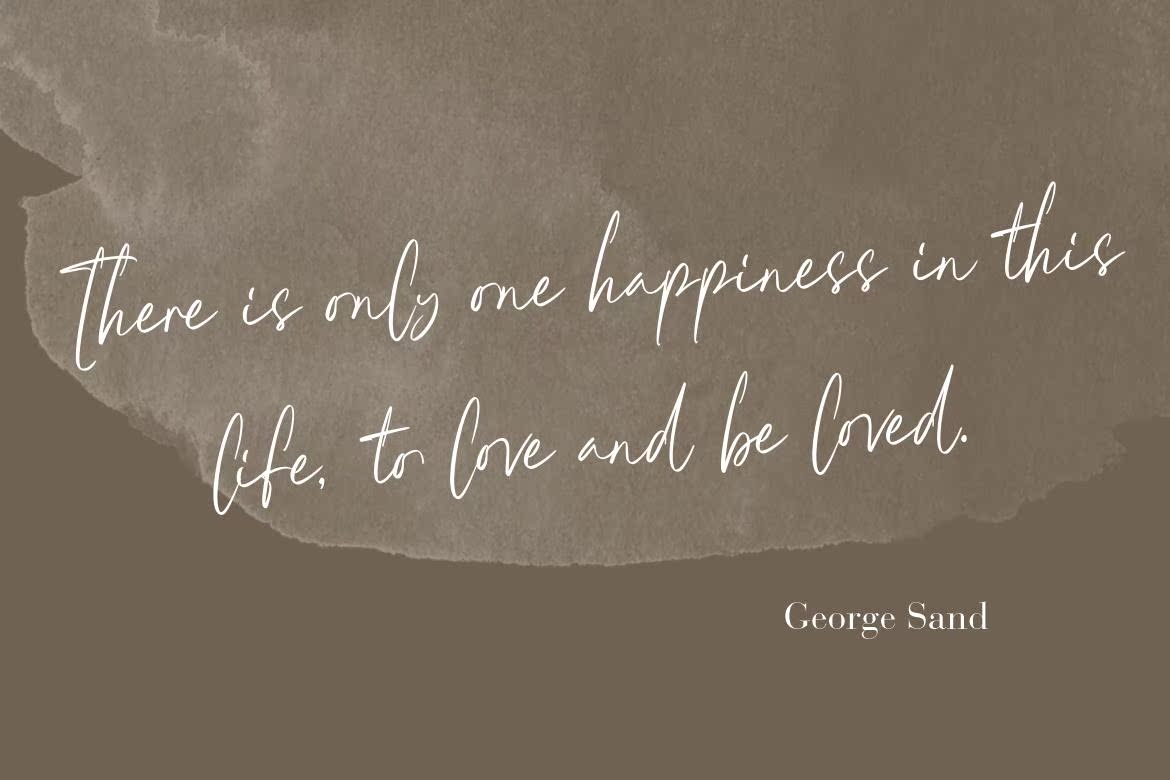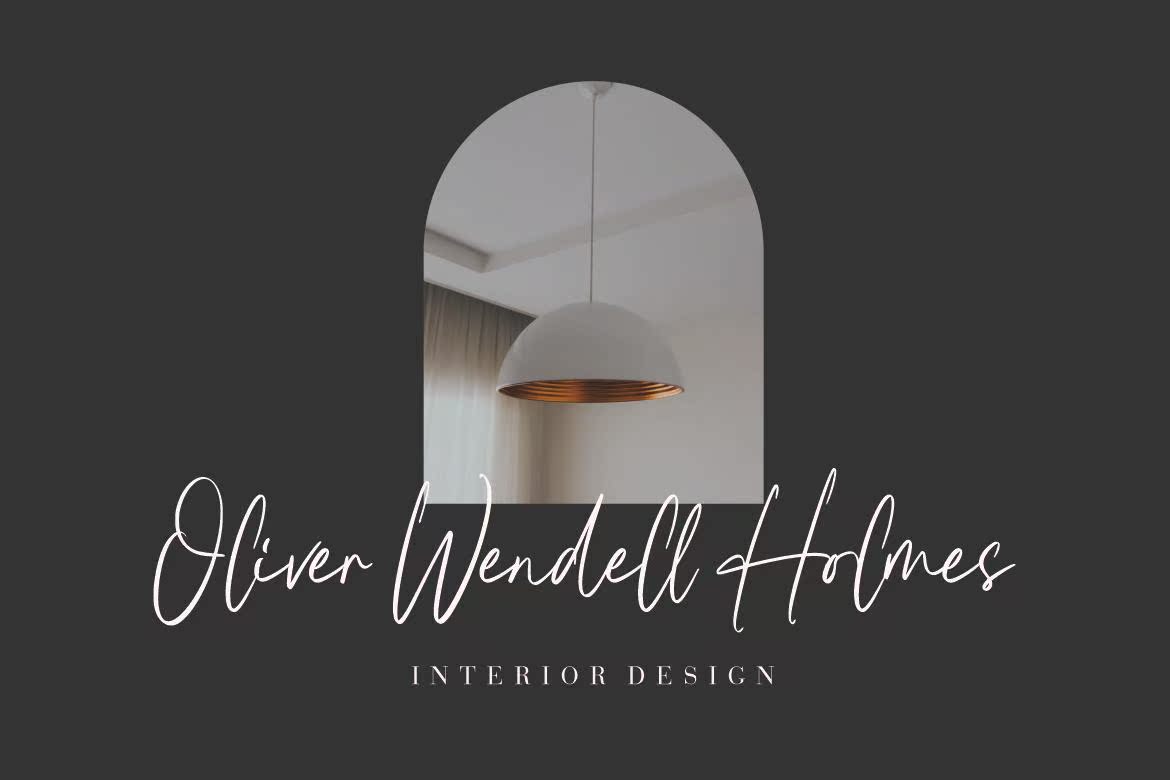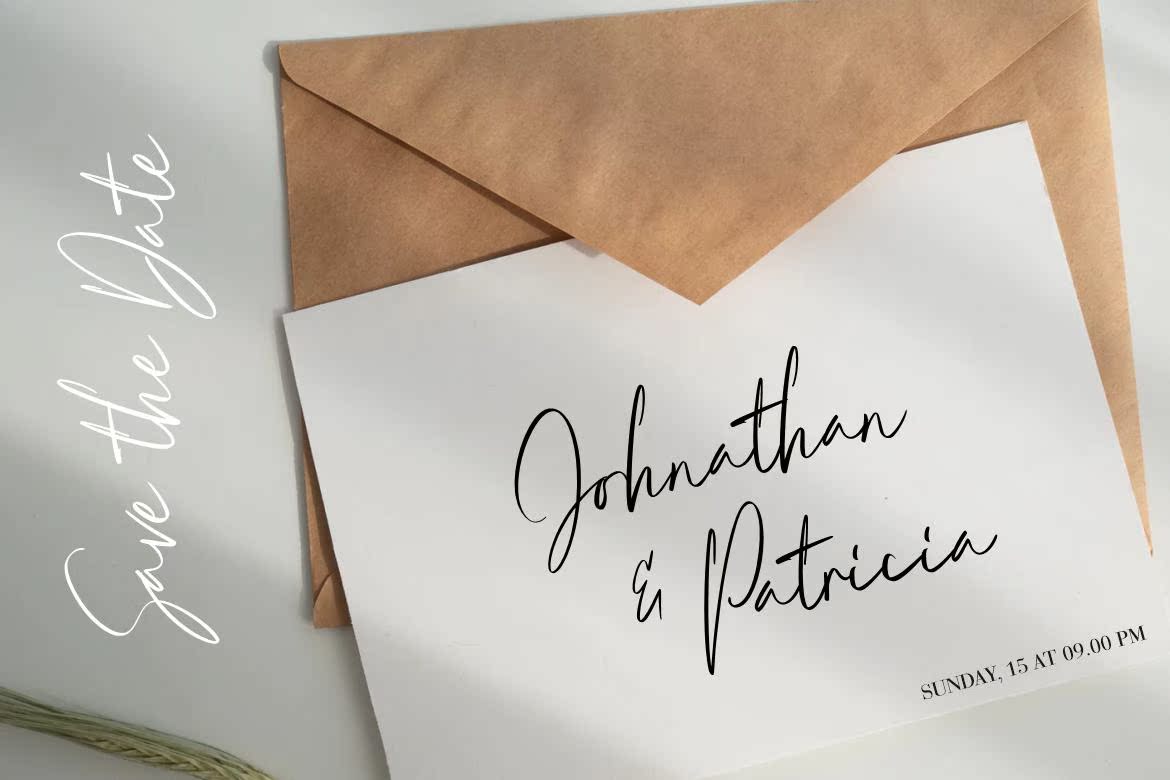
HalimasofRiastylishandFinedHandWrittenFont.It looks美丽的设计多样性要求个性化风格,如婚礼庆典、感谢卡、婚礼、问候卡、标志等等。HalimasofRiastylishandFinedHandWrittenFont.Itlooks美丽的设计多样性要求个性化风格,如婚礼庆典、感谢卡、,婚礼、问候卡、标志等等。